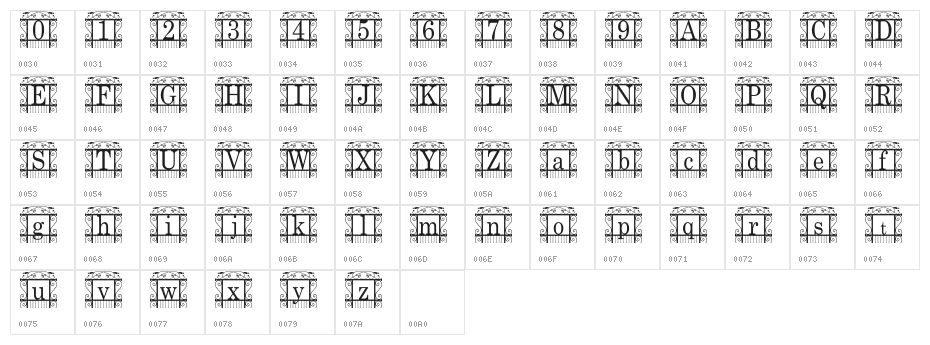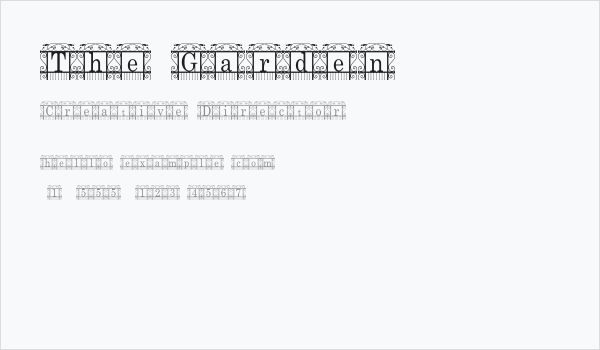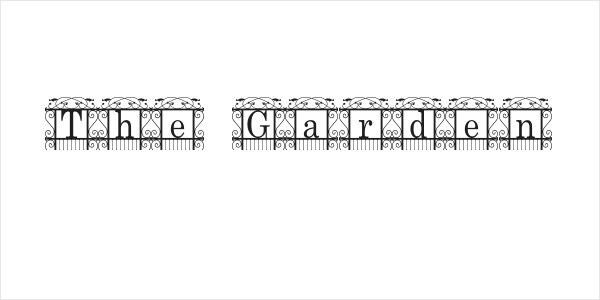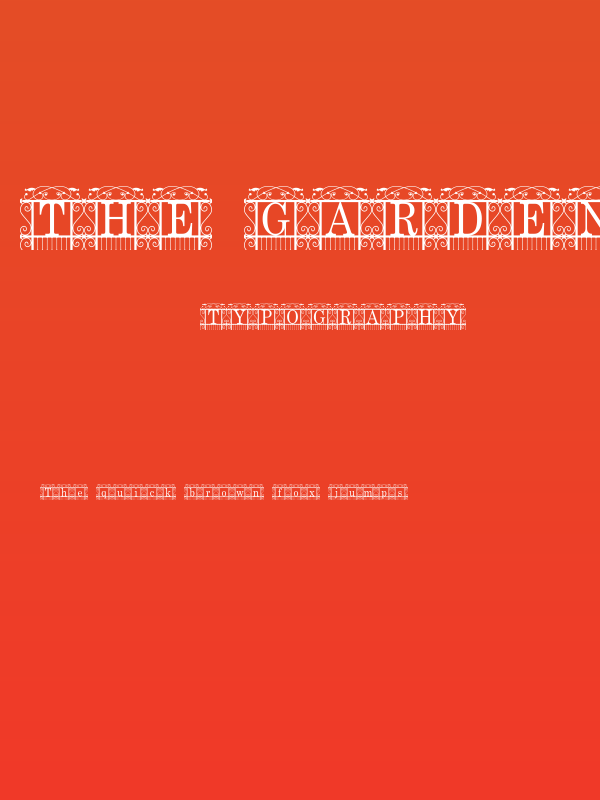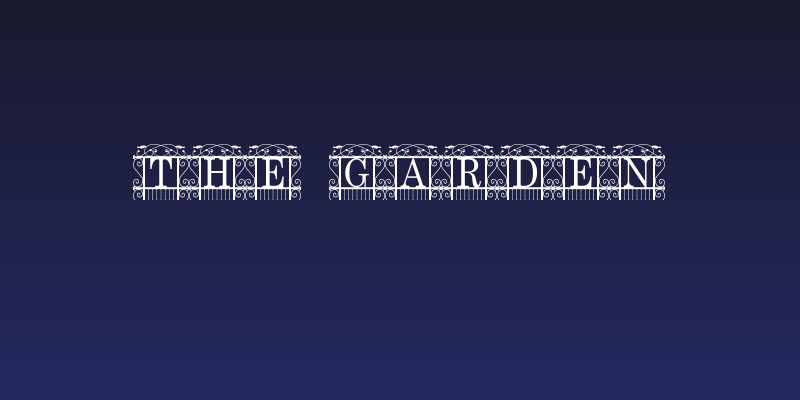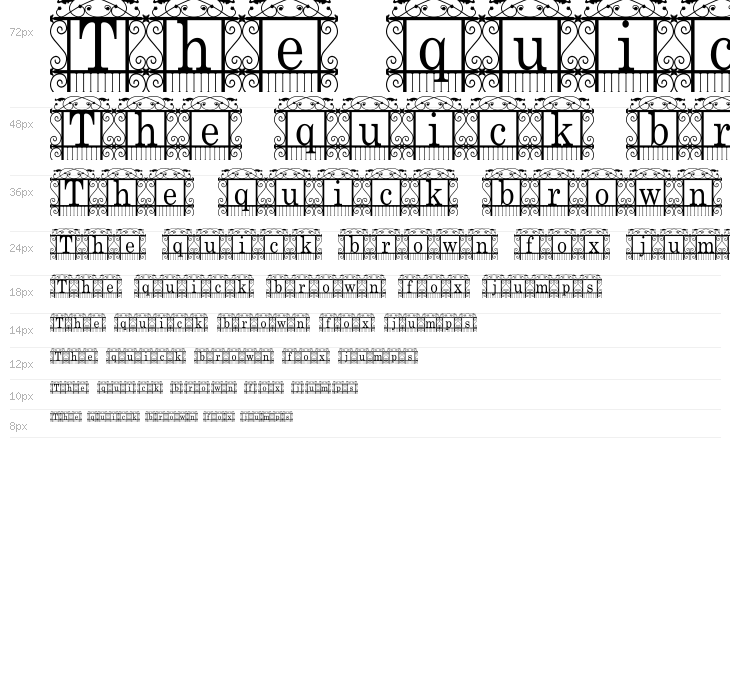
The Garden Font
| Caso d'uso | Logos, Headlines, Decorative text |
| Progetti proposti | Ideal for wedding invitations, garden-themed events, vintage posters, and decorative signage. |